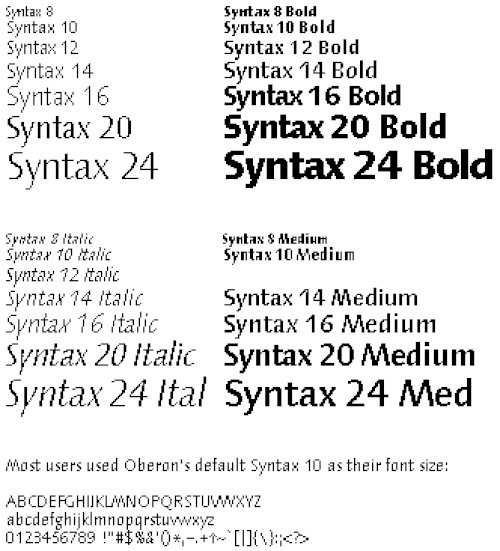
Syntaxは、スイスの書体デザイナー、ハンス・エドゥアルト・マイヤーによってデザインされたフォントファミリーです。当初はサンセリフフォントのみでしたが、後にセリフ体デザインが追加されました。
Syntaxは、1968年にMeierによってデザインされ、1969年にフランクフルト・アム・マインのD. Stempel Schriftgießerei(活字鋳造所)によってリリースされたヒューマニスト・サンセリフ書体です。 [ 1 ] [ 2 ]これは、D. Stempelが鋳造用にデザインおよびリリースした最後の書体であると考えられています。
オリジナルのデザインは1954年に作成されました。まず筆で文字を書き、次に基本的な線形を描き直し、最後に骨格にバランスよく太さを加えることで、視覚的に単線に見える文字の形を作り出しました。1968年から1972年にかけて、マイヤーはSyntax書体の追加ウェイトとバリエーションの開発に取り組みました。1989年には、オリジナルの鋳造金属デザインがAdobeによってデジタル化され、太字と極太字のウェイトも追加されました。その結果、4つのローマン体と1つのイタリック体(最も細いウェイト)からなるフォントファミリーが誕生しました。
メイアーは、Syntaxを、 SabonやBemboに似た、ルネッサンス時代のセリフ書体をモデルにしたサンセリフ書体だと説明した。大文字は幅広で、終端がベースラインと平行ではないため、躍動感がある。小文字のaとgは、2階建ての古いスタイルを踏襲している。イタリック体は、小文字のイタリック体qに見られるようなヒューマニスト・イタリック体と、小文字のイタリック体aに見られるようなインダストリアルまたはグロテスク・サンセリフ体の斜体を組み合わせたもので、FF Scala SansやGill Sansのような他のヒューマニスト・サンセリフ書体とは異なり、2階建てを維持している。FF Scala SansやGill Sansでは、aは1階建てのイタリック体になっている。
リリース時にヤン・チヒョルトはSyntaxを「非常に読みやすく、デザインも優れている。関連するGill Sansよりも優れている」と称賛した。[ 3 ] [ 4 ]
Bitstream社は、Humanist 531という名称でSyntaxをリリースしました。このフォントファミリーにはイタリック体は含まれていません。
Infinitypeは、イタリック体とミディアム体を含むフォント「Saxony」を「Syntax」という名称でリリースした。
キリル文字版は1999年にパラタイプ社でイサイ・スルツカー[ 5 ]とマンベル・シュマヴォニャンによって開発されました。
Syntaxフォントファミリーは、Niklaus WirthによってOberonオペレーティングシステム用に選ばれました。Oberonの開発期間中、MeierはETHのWirthの研究グループで、 Syntaxフォントの手動最適化ビットマップ版の開発に携わっていました(これはフォントのアンチエイリアシングが普及する以前のことです)。
1995 年、ハンス・エドゥアルト・マイヤーとライノタイプは Syntax フォント ファミリーの大幅な改訂と拡張を開始しました。[ 6 ]オリジナルのフォント デザインに基づいて、ホットメタルおよびフォトタイプセッティングマシンに対応するために行われた変更は破棄されました。ファミリーは 6 つのウェイトに拡張され、すべてのウェイトにイタリック体が含まれています。すべてのフォントにはオールド スタイル数字とプロポーショナル ライニング数字が含まれており、最も軽い 3 つのウェイトにはスモール キャップグリフも含まれています。レギュラー ウェイトとボールド ウェイトのフォントにはキリル文字も含まれています。@、C、R、 fi、flなどの文字は再設計されました。
このフォントファミリーは2000年にリリースされました。
Linotype Syntaxの派生フォントですが、古代ギリシャの彫刻文字をモデルにしています。Linotype Syntax Lapidarは、Linotype Syntax Lapidar TextとLinotype Syntax Lapidar Displayの2種類のデザインで提供されています。
これは、セリフ体を含むLinotype Syntaxの派生フォントです。サンセリフ体と同様に、テキスト用とディスプレイ用のデザインが用意されており、フォントファミリーごとに同じ数のフォントが収録され、同じ文字セットをカバーしています。ただし、Linotype Syntax Lapidar Serif Displayはタイトル大文字をサポートしていません。
これは、ローマのラスティック体大文字のスタイルを模したLinotype Syntaxの派生フォントです。このフォントファミリーは6種類のウェイトがあり、すべてのウェイトにイタリック体フォントが用意されています。ISO Adobe 2、Adobe CE、Latin Extendedの文字セットに対応しています。OpenType機能として、オールドスタイル数字も含まれています。
これは、セリフ付きのLinotype Syntaxの派生フォントです。このフォントファミリーは6種類のウェイトがあり、すべてのウェイトに補完的なイタリック体フォントが用意されています。ISO Adobe 2、Adobe CE、Latin Extendedの文字セットに対応しています。OpenType機能として、オールドスタイル数字、スモールキャップ、そして最も軽い3つのウェイトにはプロポーショナルライニング数字が含まれています。
これは、オリジナルのSyntaxをベースに、Nadine Chahineがデザインしたアラビア語版フォントです。アラビア語で「砂漠」を意味するBadiyaは、現代的でやや変化を加えたNaskhフォントです。このデザインは、カウンター部分が開いているため、非常に小さなサイズでも使用でき、雑誌や企業コミュニケーションにおける印刷物に最適化されています。
標準と太字の2種類のローマンフォントが作成されました。ISO Adobe 2、ラテン拡張文字、アラビア語、ペルシア語、ウルドゥー語の文字、および対応言語の表形式数字をサポートしています。
Linotype Syntaxは、TDC 2 2000(Type Directors Club Type Design Competition 2000)のテキスト/ディスプレイ書体システム部門で賞を受賞しました。[ 7 ]
Bitstream Humanist 531 Cyrillic は、Kyrillitsa'99 のテキスト部門で賞を受賞し、[ 8 ]また「bukva:raz!」タイプデザインコンテストでも受賞しました。[ 9 ] [ 10 ]
Linotype Syntaxは、OÖ Nachrichten、Deccan Herald新聞、Lonely Planetガイドブック[ 11 ] 、impuls 2000雑誌[ 12 ] [ 13 ]で使用され、 Sinclairコンピュータのボックスアート、マニュアル、パンフレットにも使用されました。